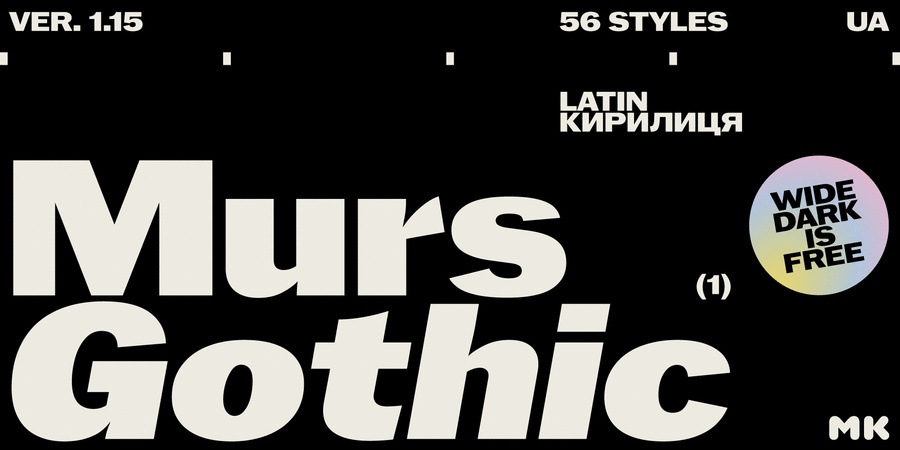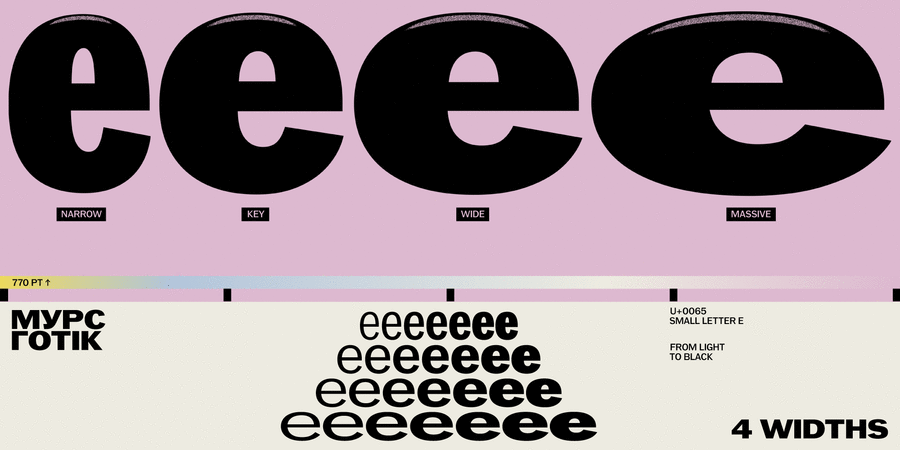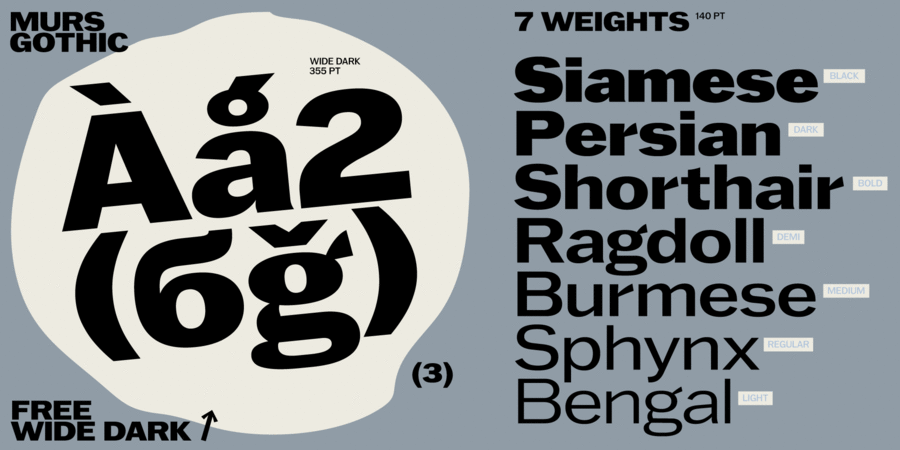
Murs Gothic – це сміливий гротеск із гострими динамічними формами. Це збірний образ американських шрифтів без засічок (які там називають Gothic) 19-го і початку 20-го століть. Шрифт досить масивний, має щільні інтервали між літерами та підвищену контрастність. Деякі витягнуті, а також асиметричні деталі надають йому характерної емоційності та грайливості. Це особливо помітно на тлі популярних нейтральних геометричних гротесків.
Кожне накреслення містить 694 гліфи, серед яких латинські та кириличні символи, пара лігатур, альтернативи, геометричні символи, стрілки та багато іншого!
Шрифтове сімейство Murs Gothic складається з 56 накреслень, які регулюються за вагою та шириною + курсивні накреслення. Також є варіативний шрифт із 3 осями. Це дозволяє гарнітурі бути дуже гнучкою та адаптуватися до багатьох різних дизайнів.
Асоціації з сімейством шрифтів Murs GothicОсобистість і характер гарнітури:
якісний, чіткий, самостійний, західний, твердий, гострий, модний, різкий, тонкий, формальний, рівний, зрозумілий, технічний, практичний, доступний, стійкий, серйозний, міський, діловий, прагматичний, динамічний, значний, надійний, побутовий, консервативний, гучний, сміливий, переконливий, мотивуючий, колючий, сильний, солідний, крутий, сталевий, залізний, амбітний, блатний, бандитський, гангстерський, впевнений, урбаністичний, наполегливий, строковий, дерев'яний, прямокутний, авторитетний, суворий, робочий, грубий, брутальний, міцний, мужній, кондовий, потужний, помітний, яскравий, активний, важливий, чорний, важкий, дзвінкий, ризикований, агресивний, зухвалий, кричущий, жорсткий, екстремальний, тісний, радикальний, Простий, звичайний, непомітний, цікавий, оригінальний, характерний, незвичайний, самобутній, популярний, кінематографічний, претензійний, екстравагантний, нонконформістський, здоровий, мачо, щедрий, виразний, рясний, насичений, енергійний, нахабний, сексуальний, запальний, швидкий, рішучий, дотепний, стрімкий, швидкісний
дизайн, Місто, бізнес, дім, побут, карти, Барбершоп, паровоз, новини, політика, гроші, торгівля, кіно, одяг, інструмент, м'ясо, мафія, обід, вечеря, взуття, концерт, селфі, цигарки, магазин, хмарочос, промисловість, будівництво, деревина, механіка, ремонт, цегла, вантажівка, далекобійник, сталевар, робочий, детектив, порт, завод, металургія, енергетика, електростанція, верстат, кінотеатр, розваги, реклама, каскадер, екстрим, бомба, шоу, аптека, меблі, гра, джинси, револьвер, гамбургер, Інстаграм, поліція, казино, мотор, атракціон, блокбастер, бойовик, екшен, позашляховик, паливо, авто, тачки, автомобіль, швидкість, шахта, екскаватор, вантажоперевезення, прес Гарнітура має ознаки стилів: